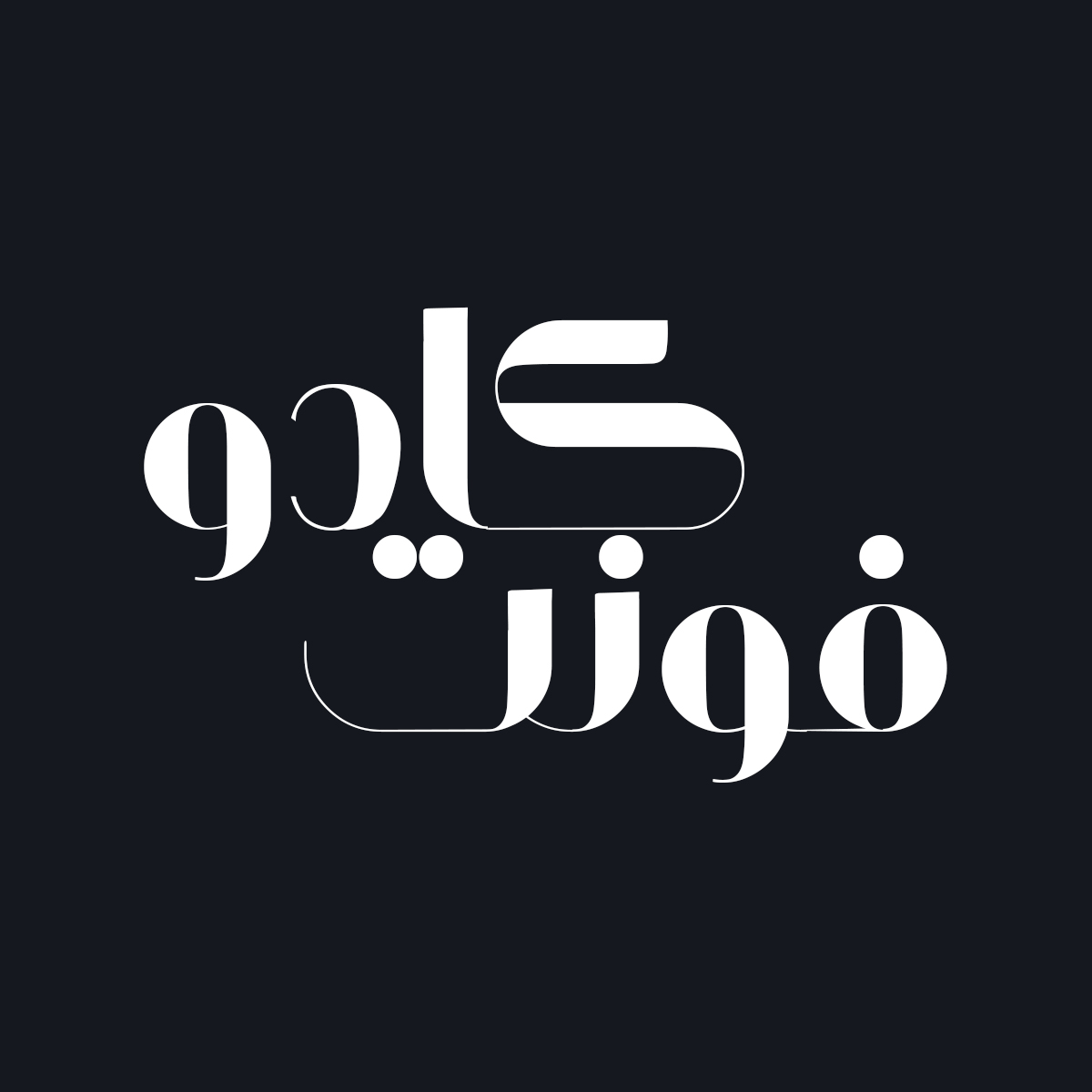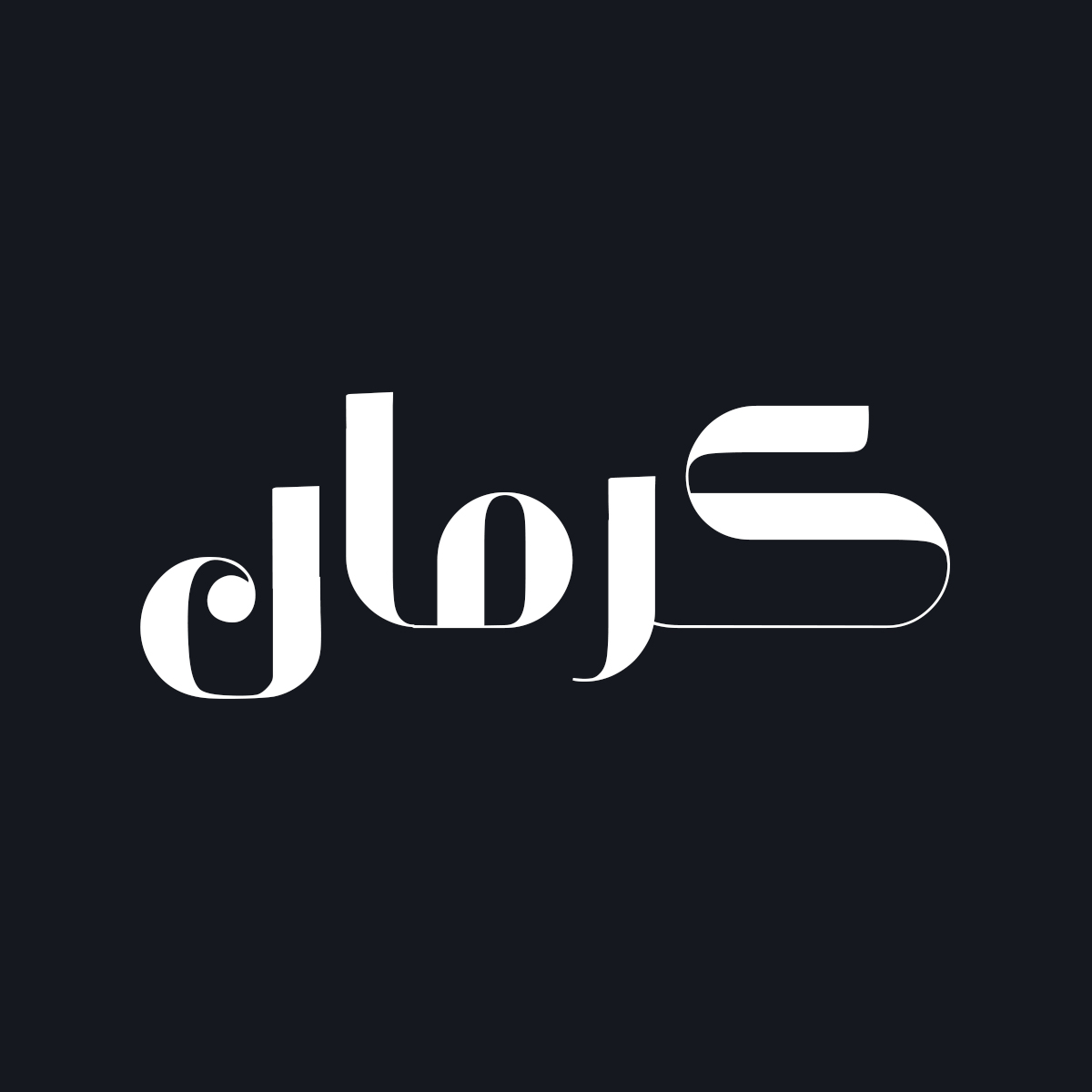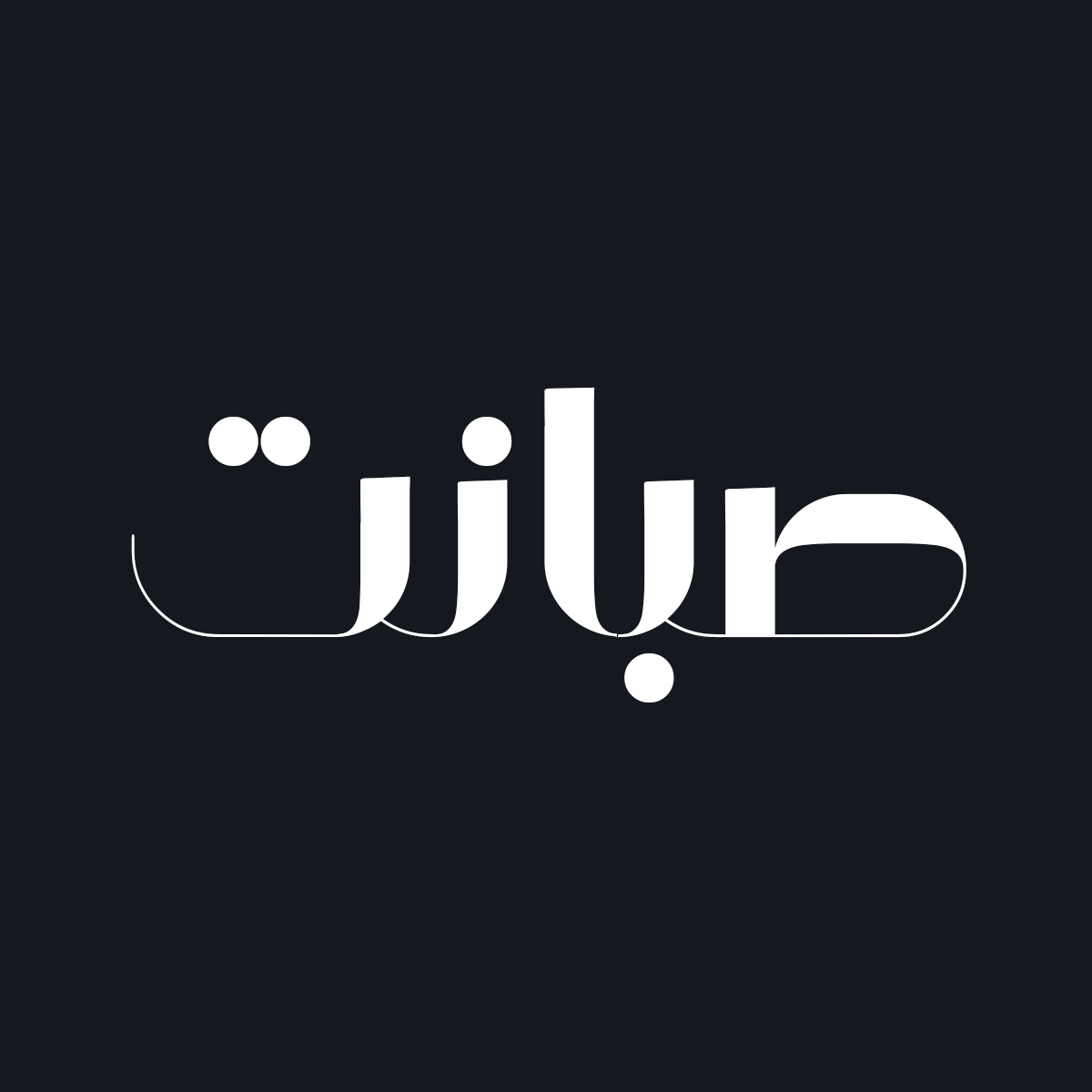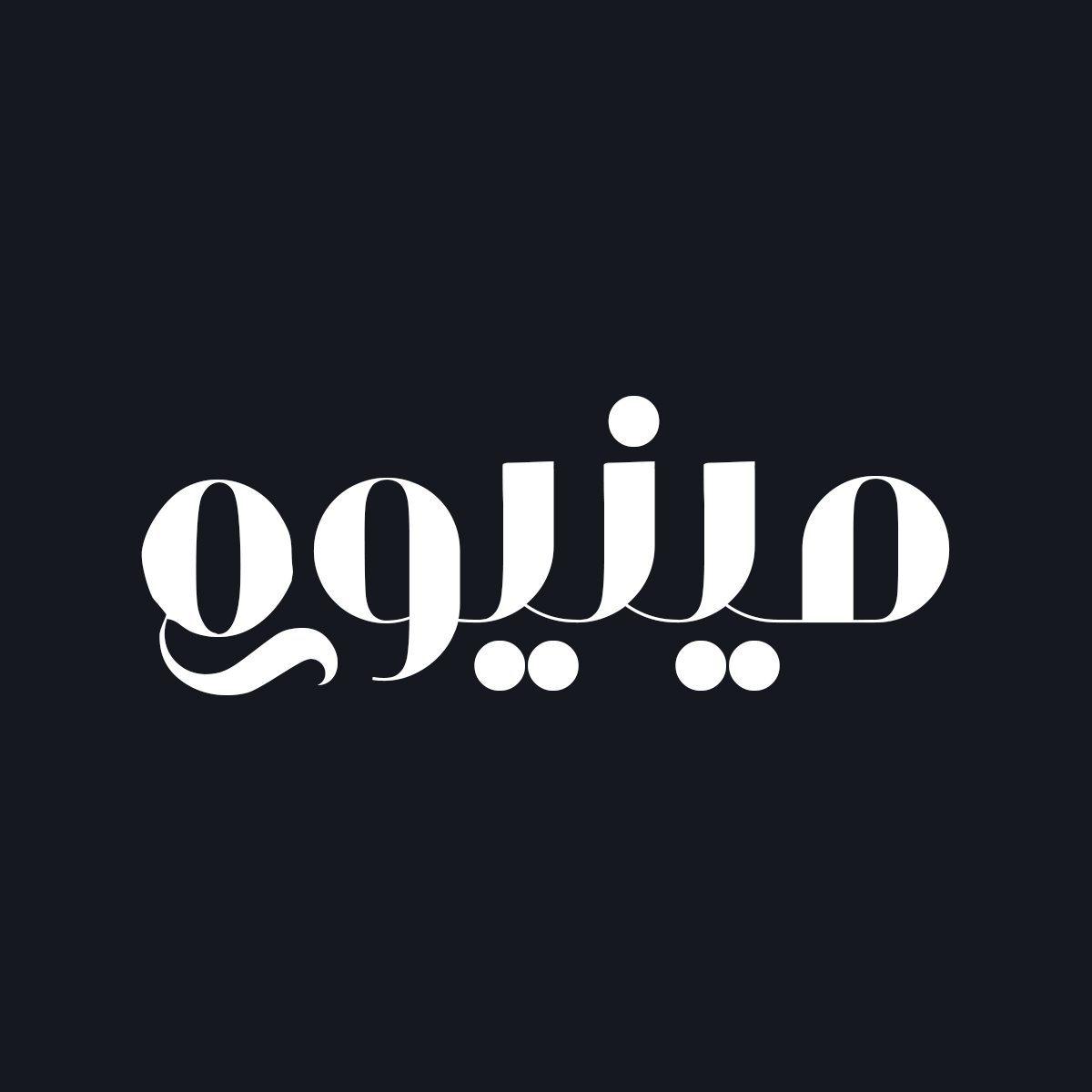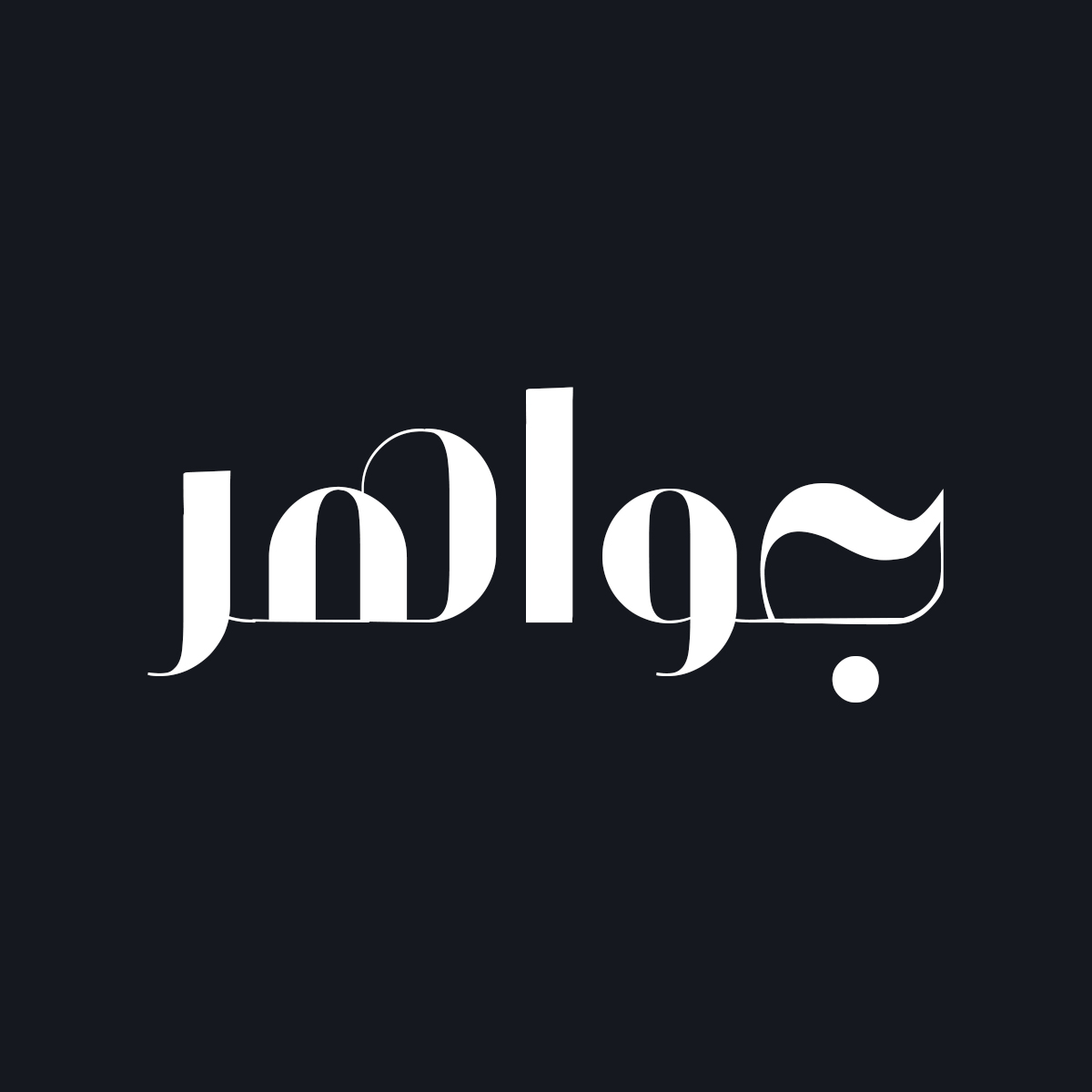
از فونت فارسی کادو برای طراحی لوگو، بنر، طراحی پوستر و متن استفاده کرد و این به جهت شکستگیها و انحناهای متعادل، همنشینی روان حروف در کنار هم، حجم دهی بالا و اتصالات مختلف است. در ادامه برای شما نمونه تایپ های این محصول حرفه ای رو آماده کردیم که میتونید مشاهده کنید.
پیشنمایش و نمونه تایپ های فونت کادو